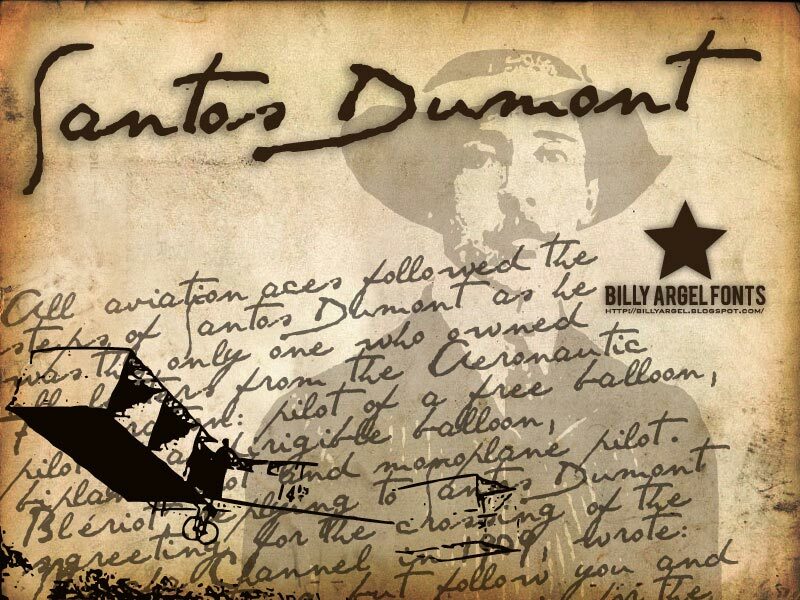
SANTOS DUMONT
Santos Dumont od Billy Argel to darmowy krój pisma odręcznego o luźnym, zwiewnym rytmie kursywy. Litery sprawiają wrażenie szybko nakreślonych i lekko połączonych, z długimi, zamaszystymi pociągnięciami i otwartymi pętlami, co nadaje im nieformalny charakter – niczym notatka na marginesie.
Idealnie nadaje się do metek odzieżowych, identyfikacji wizualnej kawiarni, nagłówków zaproszeń, okładek książek i grafik z cytatami, gdzie darmowy font ma wprowadzić dynamikę, a nie tylko wygładzone wykończenie. Wykorzystaj go do podpisów, tytułów czy krótkich napisów na opakowaniach, gdzie wydłużone znaki mogą swobodnie prowadzić oko po projekcie, budując wizualny klimat.